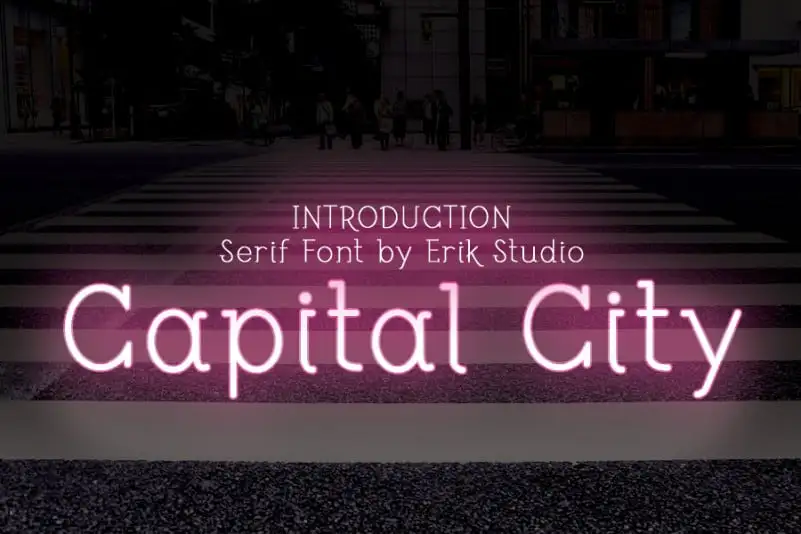
A Capital City Display Font é uma elegante fonte de display que traz alegria aos seus projetos digitais. Com sua personalidade única e vibrante, ela irá dar um toque fresco e contemporâneo a qualquer trabalho criativo. Suas linhas vivas e arredondadas são ideias perfeitas para quem busca algo mais moderno em seus materiais de design gráfico. Adicione esta fonte ao seu próximo projeto e observe como ela torna suas ideias destacar-se da multidão. Não deixe que seu trabalho fique sem vida, permita a Capital City Display Font dar vida às suas criações!